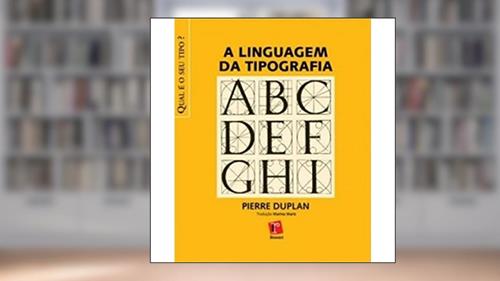
Tópicos de A Linguagem da Tipografia - Pierre Duplan Aprofunde-se nos tópicos essenciais de 'A Linguagem da Tipografia' de Pierre Duplan e descubra como a tipografia transforma a comunicação visual. terça-feira, 21 de janeiro de 2025 Introdução à Tipografia: Entenda a importância da tipografia na comunicação visual e como ela influi na percepção do texto. História da Tipografia: Uma breve linha do tempo mostrando a evolução da tipografia desde os primeiros tipos móveis até as modernas fontes digitais. Elementos Básicos: Conheça os elementos que compõem a tipografia, como fonte, tamanho, espaçamento e alinhamento, e como eles se relacionam. Classificação das Fontes: Descubra os diferentes tipos de fontes e suas características, como serifadas, sem serifa e display. Legibilidade e Leiturabilidade: Entenda as diferenças entre legibilidade e leiturabilidade, e como isso afeta a escolha das fontes para diversos meios. Composição Tipográfica: Aprenda as regras de boa composição tipográfica, incluindo a hierarquia visual e a criação de contraste. Aplicações Práticas: Explore como a tipografia é aplicada em diferentes contextos, como impressos, web design e branding. Cor e Tipografia: Veja como o uso de cores pode alterar a impressão que uma tipografia causa e a importância de um bom contraste. Erros Comuns: Conheça os erros mais comuns na tipografia e como evitá-los para garantir uma comunicação eficaz. Tendências Atuais: Fique por dentro das tendências contemporâneas na tipografia e como elas estão moldando o design hoje. Em "A Linguagem da Tipografia", Pierre Duplan nos apresenta de forma dinâmica e envolvente o universo da tipografia, mostrando que não se trata apenas de letras, mas de uma forma poderosa de comunicação. A obra é rica em exemplos visuais que ilustram os conceitos e técnicas discutidos, tornando o aprendizado mais tangível. Se você busca refinar suas habilidades em design ou entender melhor como a tipografia pode impactar a mensagem que você quer transmitir, essa leitura é indispensável! 📚✨️ Ao ler este livro, tive a oportunidade de aprimorar meu olhar crítico sobre as letras e suas aplicações, e com certeza me deixará mais atento às sutilezas do design. Não perca a chance de fazer dessa obra uma parte do seu conhecimento! Ver Descontos Desconto Você quer um descontão para comprar o livro 📖 A Linguagem da Tipografia? Veja como conseguir: Não é necessário digitar nenhum código de cupom; O desconto aparecerá já aplicado na página do livro, ao lado do preço, quando você abrir o site da Amazon.com.br através do link abaixo; Este link também pode acionar descontos em outros produtos da Amazon à medida que você ali navega; Vale para outros livros, eletrônicos e outros; Os descontos têm validade apenas no dia do acesso (hoje), mas podem expirar a qualquer momento sem aviso prévio; O valor e validade dos descontos são definidos a critério exclusivo do site Amazon.com.br; Este site não participa de quaisquer transações comerciais feitas por você no site Amazon.com.br, embora recomendemos a loja; Caso não apareça nenhum desconto, é porque o mesmo já expirou. Mas pode haver descontos em outros itens... ➡️ Copie e cole o link abaixo: Ver na loja Enzo Silva Transformo os livros que eu gosto em tópicos para ajudar as pessoas a priorizarem suas leituras. Desde a escola meus colegas adoravam estudar através dos meus resumos, então acho que levo jeito...Finalizando o Ensino Médio numa escola pública, pretendo estudar e seguir carreira em Marketing Digital.